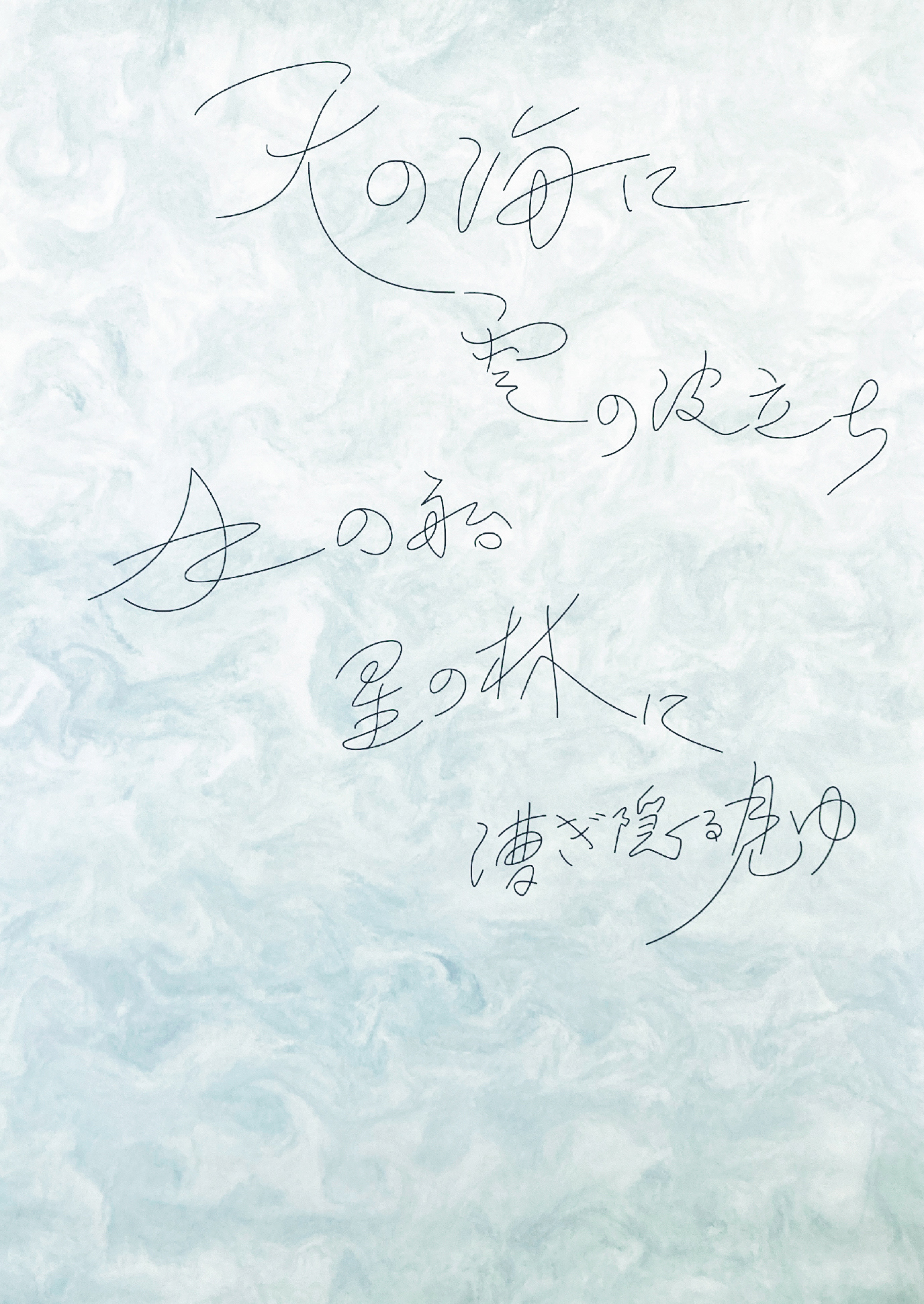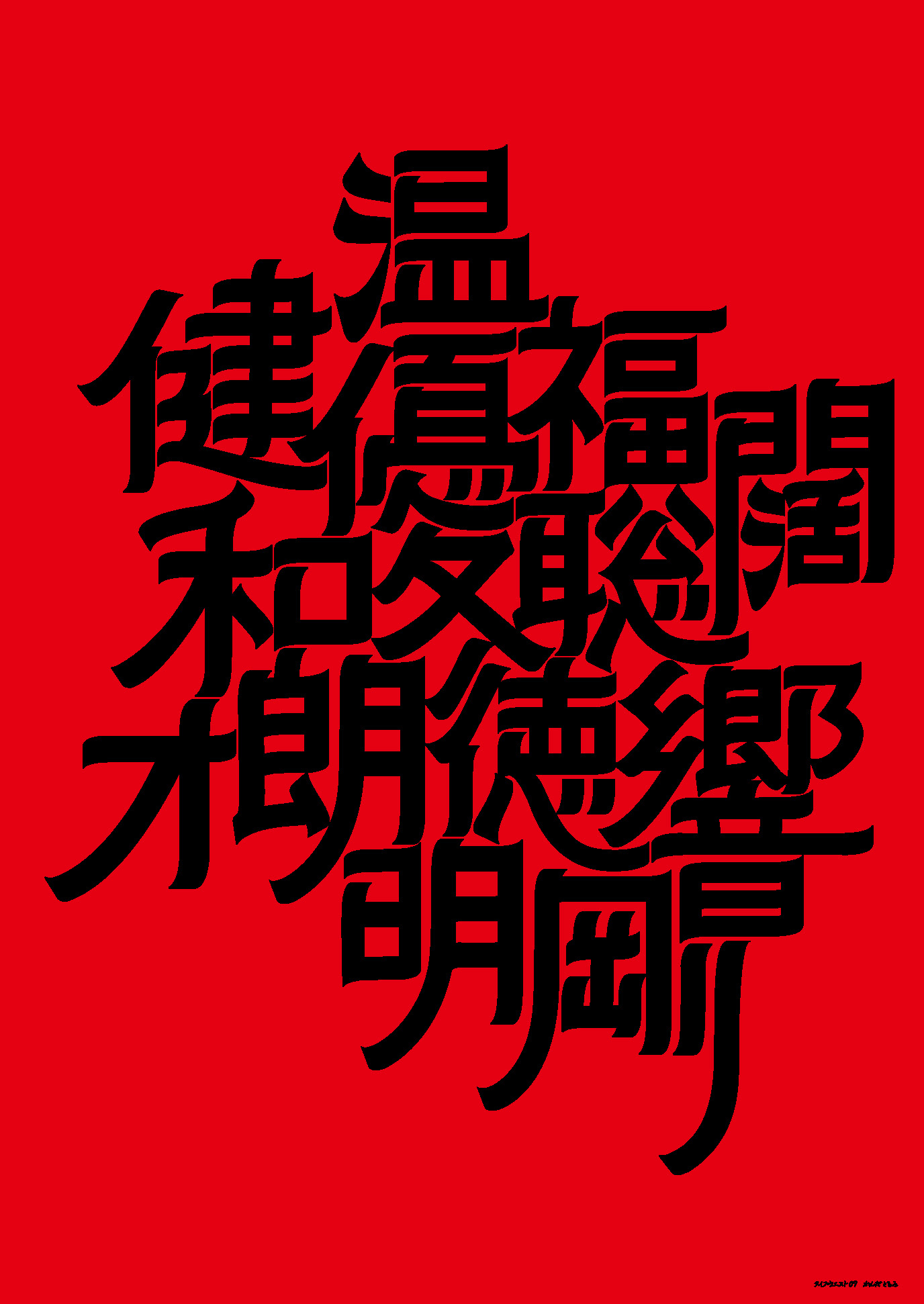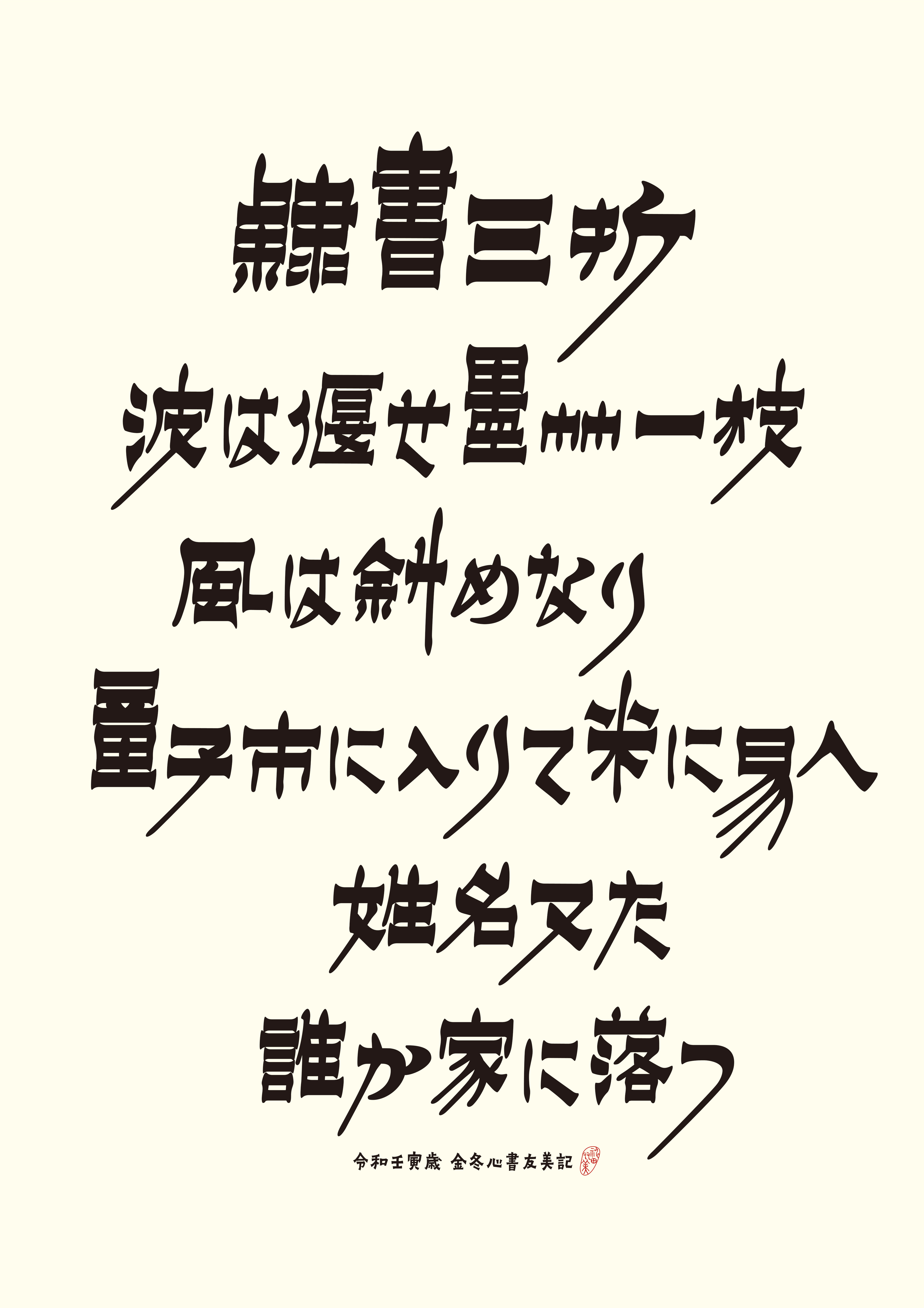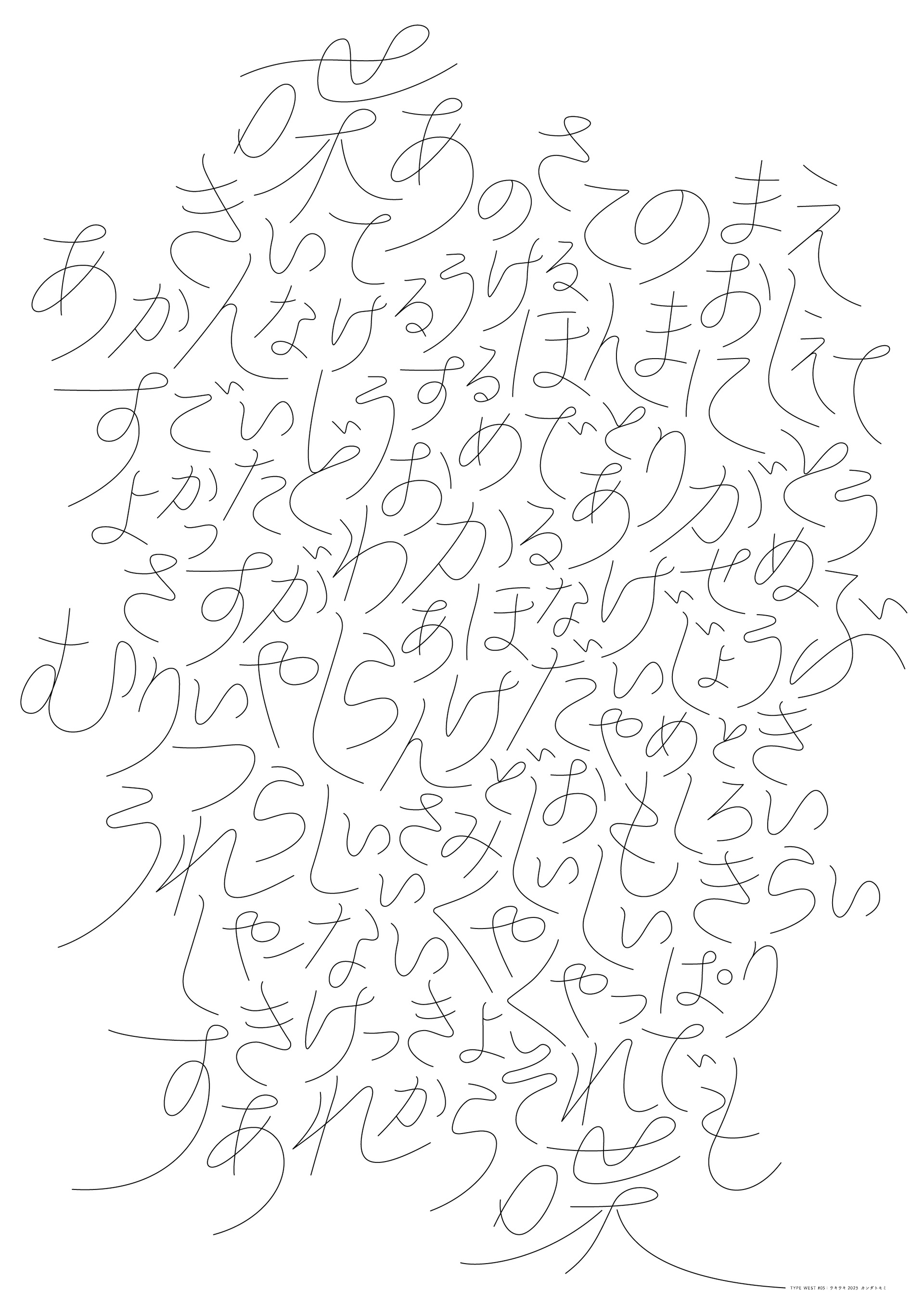
日本タイポグラフィ協会西部研究会が主催するポスター展のための作品です。毎年提示されるテーマに合わせて、モノクロで自由に表現。私は「書体と書道の間」を意識して、自由な文字の集まりをテーマに製作しています。
TYPE WEST #05ポスター[お喋り」
TYPE WEST #04ポスター[文字旅の門出]
TYPE WEST #06ポスター[つづる言葉]
TYPE WEST #07ポスター[重なる連なる]